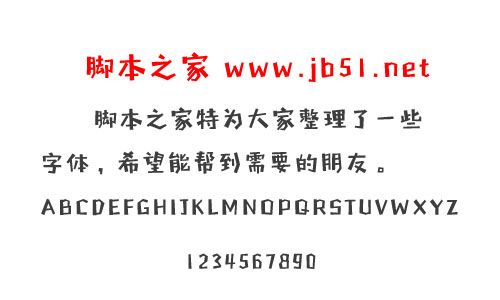
字體管家方萌簡字體是一款卡通POP字體,字體富有變化,字形充滿童趣,整體散漫隨意,識別度非常高,適合兒童產(chǎn)品畫冊、兒童產(chǎn)品包裝設(shè)計(jì)、海報(bào)設(shè)計(jì)、網(wǎng)頁標(biāo)題設(shè)計(jì)等應(yīng)用,本站提供了字體管家方萌簡字體下載,歡迎有需要的朋友前來下載使用。